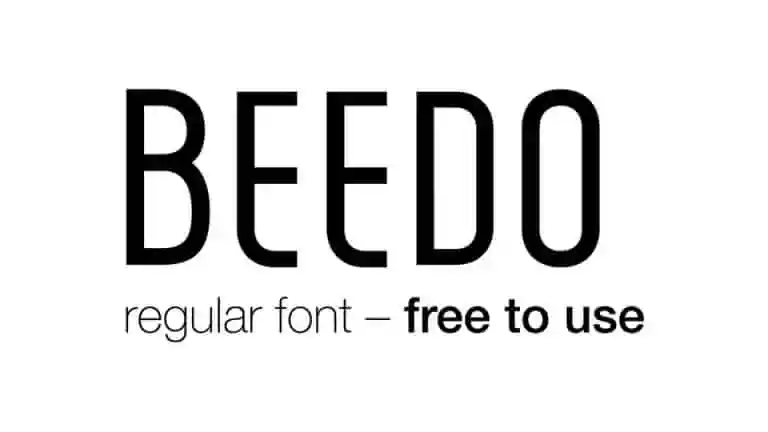
Beedo Display Font – Download Grátis
A Beedo Display Font é uma tipografia sans-serif moderna e minimalista que busca trazer serenidade à sua obra de design. Com linhas geométricas e um visual limpo e modular, esta fonte foi criada por Lenka Volková, designer do 99designs. É especialmente apropriada para criar logotipos, marcas de identidade corporativa, headlines e materiais de marketing tanto para web quanto impressão. Suas formas altas e retangulares tornam-na uma excelente opção para qualquer tipo de design minimalista. Seja ela o fundo de um site moderno ou a fonte do seu próximo adesivo de camisa, Beedo Display é uma escolha versátil que se adapta perfeitamente aos estilos mais atuais e contemporâneos do desenho gráfico.